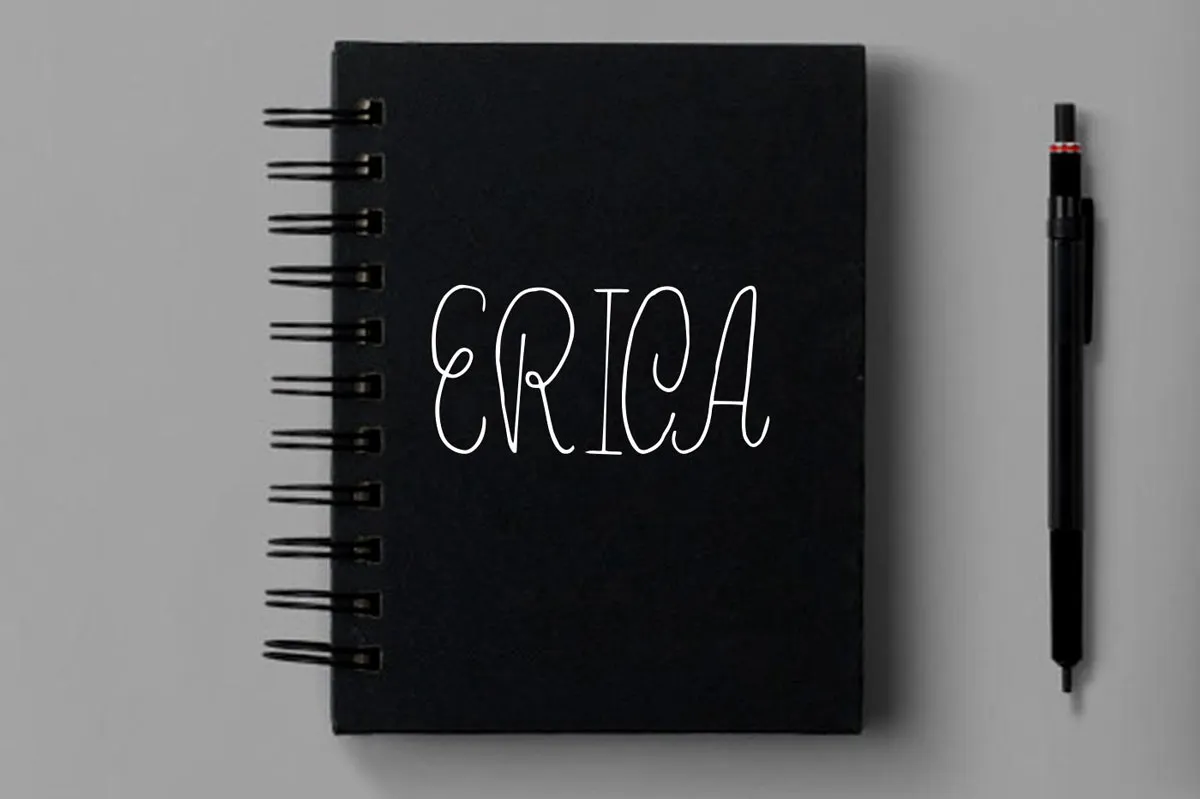
Erica Handwritten é uma fonte curvilínea e autêntica que inspira a mão humana. Desenvolvida pelo designer creativetacos, ela captura as nuances naturais do estilo handwritten de escrita diária. Erica não apenas adiciona um toque pessoal aos seus projetos, mas também simplifica o processo de criatividade em seu trabalho. É perfeito para criar uma identidade única e distintiva nos mais diversos formatos, desde logotipos e selos até cartazes e camisetas. Suas linhas simples e divertidas facilitam a utilização da fonte, tornando-a ideal para estilos de design como logos, selos, embalagens, headlines, cartazes, camisetas, cartões de agradecimento e convites de casamento. Seja você um designer ou artista, Erica é uma escolha óbvia para incorporar ao seu estilo pessoal.